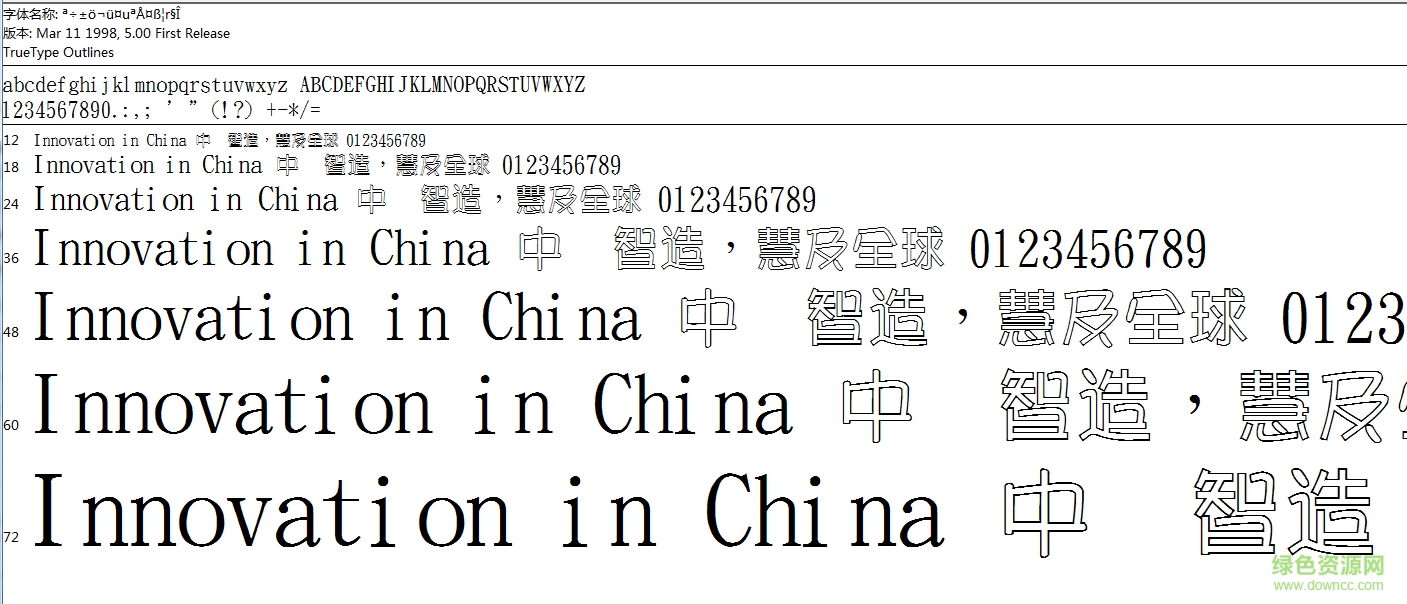
金梅美工空心字形字體是一款采用空心設(shè)計(jì)的標(biāo)準(zhǔn)字體。該字形端正大方,適用于印刷包裝、平面設(shè)計(jì)、電視廣告、報(bào)刊雜志等行業(yè),讓你的每種設(shè)計(jì)都能煥然一新,快來綠色資源網(wǎng)下載使用吧
該字體由空心線條構(gòu)成,字形端莊雄秀,神韻超逸,結(jié)體嚴(yán)整,看上去十分美觀,整體效果非常統(tǒng)一,且字庫完整